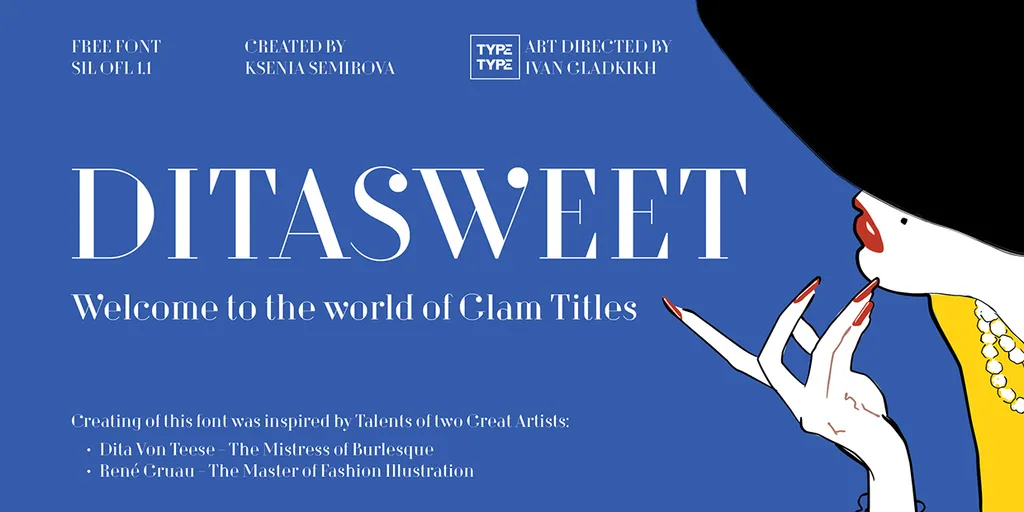
A fonte Dita Sweet é uma elegante escolha para projetos visuais que exigem glamour e sofisticação. Desenvolvida pelo designer Hamilton, essa fonte foi criada especialmente para os ambientes de mídia visual mais elaborados, como posters luxuosos ou títulos em revistas caras. Com traços finos e uma tipografia fluida, Dita Sweet não apenas destaca o texto, mas também transmite um toque refinado que se encaixa perfeitamente para ambientes festivos e de alto padrão. Inspirada na elegância dos anos 20, essa fonte é ideal para criar títulos chamativos em revistas ou para adicionar personalidade a qualquer projeto de marketing visual. Seja você um designer gráfico buscando uma maneira criativa de destacar suas criações ou simplesmente alguém que aprecia a sofisticação e o luxo, Dita Sweet é definitivamente uma fonte de escolha.